モリサワフォント2017年新書体が発表
株式会社モリサワが2017年秋にリリースする新書体を発表した。
「君の名は。」のタイトルでも使用され、ますます評判のA1明朝の特徴を継承しつつ、柔らかな表情も見せる「A1ゴシック」、モリサワオリジナルの欧文書体として98の言語と海外の表記ルールに対応した「Citrine(シトリン)」、縦組みの際に言葉によって文字の形が変化する機能をもった「みちくさ」、歴史的な書物の字形を復刻した「きざはし金陵」、活版印刷のインクのにじみを再現した「秀英にじみ明朝」、大胆な筆使いが特徴の見出し用書体「黒曜」が対象製品であるMORISAWA PASSPORT製品、MORISAWA Font Select Pack製品、クラウドフォントサービス「TypeSquare」に収録となる。
モリサワフォント2017年新書体「A1ゴシック」
A1明朝の基本となる骨格を参照して開発されたオールドスタイルのゴシック体ファミリー。線画の交差部分の墨だまり表現や、エレメントの端々に僅かな角丸処理を加えることで温もりのあるデザインに仕上げている。
L、R、M、Bの4種類のウエイトで展開。
モリサワフォント2017年新書体「Citrine」
▼Citrine代替字形サンプル
明るく幾何学的な要素を取り入れながらも、レトロで優しい風合いをもつヒューマニストサンセリフをコンセプトに作成。A1ゴシックの和欧併記を目的に作られており、墨だまりや角丸処理といった共通のエレメントを採用。
ローマンとイタリックの各4ウエイトで展開され、海外の表記ルールを満たす文字種を多く備えている。「a」や「g」の異体字、数字のバリエーションなど、さまざまな代替字形も網羅。
モリサワフォント2017年新書体「みちくさ」
▼みちくさ連綿体サンプル
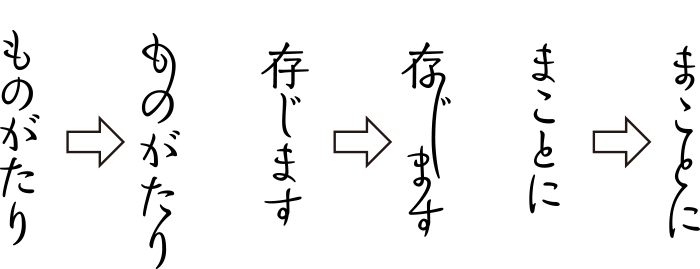
ふところを絞った骨格にやわらかく現代的なエレメントで構成された明朝体風の書体。独創的であり、豊かな表情を持つかなは、多種多様な連綿体や代替字形が用意されており、OpenType機能を使用することで縦組みの際に文脈を考慮した連綿体などを呼び出すことができる。連綿体は続け字の書体で欧文書体のスクリプト体に相当する。元々は手書き書体であり、行書体ベースのものと草書体ベースのものが存在していたがモリサワのみちくさは明朝体の連綿体になっている。
モリサワフォント2017年新書体「きざはし金陵」
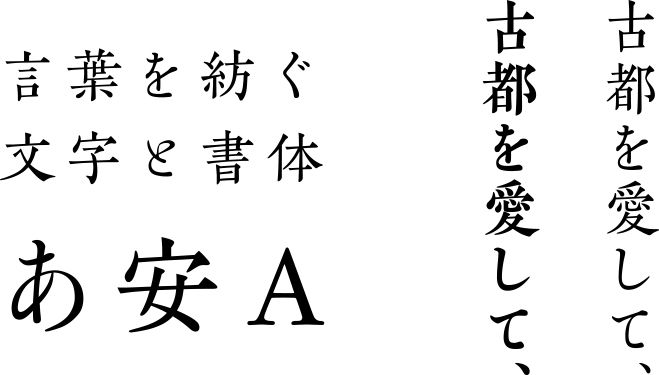
中国・明代の南京国子監で刊行された『南斉書』を元に復刻した「金陵」と1893年に東京築地活版製造所で印刷された『長崎地名考』を元に復刻した和字(かな)書体「きざはし」をマッチングした正統派のオールドスタイルの明朝体。
モリサワフォント2017年新書体「秀英にじみ明朝」
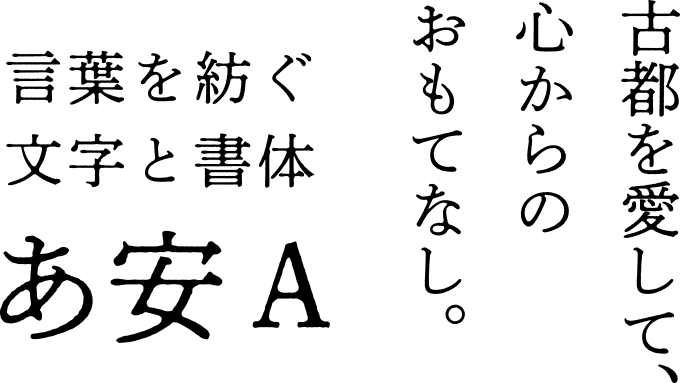
2009年にリリースとなった「秀英明朝 L」をベースに、活版印刷による紙面上でのインクのにじみを再現した書体。線画にランダムな揺らぎや太み、丸み処理を施すことで、やわらかい印象をもったアナログ感やレトロ感を演出している。
大日本印刷が開発した、にじみフォント「秀英にじみ明朝L」は2016年11月にWebフォントサービス「FONTPLUS」でリリースされていたが、いよいよモリサワ製品でも収録に。秀英体シリーズは今やフォントワークス「LETS」でも収録されるに至ったが、「秀英にじみ明朝L」も近い内に「LETS」に収録されるのかもしれない。
また「秀英にじみ丸ゴシックB」「秀英にじみアンチック」「秀英にじみ四号太かな」の3書体は2018年以降の収録になるのだろうか。
モリサワフォント2017年新書体「黒曜」
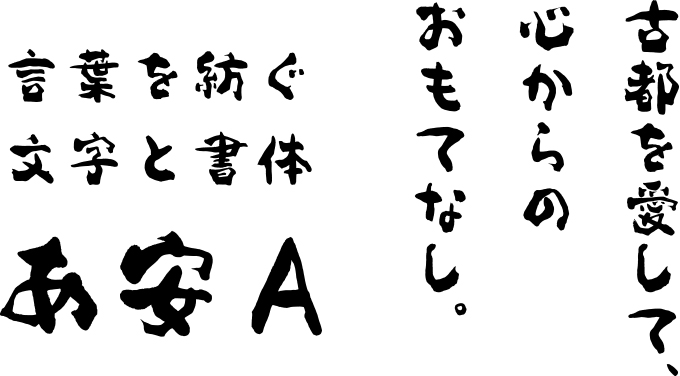
見出し用に作成された豪快でたっぷりとした黒みをもつデザイン書体。大胆な筆使いによる「はね」や「はらい」、線画の太細のコントラストが特徴。無骨で力強いイメージを表現したいシーンや題字などの大見出し、看板サインなどの利用に適している。